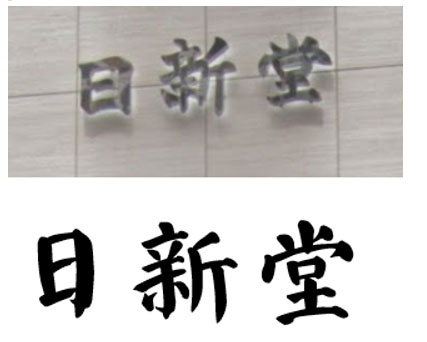
NSK白洲願法自書告身帖フォントが開発されました
中本白洲 72才にして 後世に残せるフォントに制作制作に取り組みました
NSK白洲願法告身帖フォント
顔真卿 顔
顔真卿フォントを使いますと下の様な
看板などが出来ます。
顔真卿フォントはインパクトの強い、印象に残る書体でありながら
格調ある書風です
奥皆様のポスター、表題、垂れ幕、商品の告知などに向き